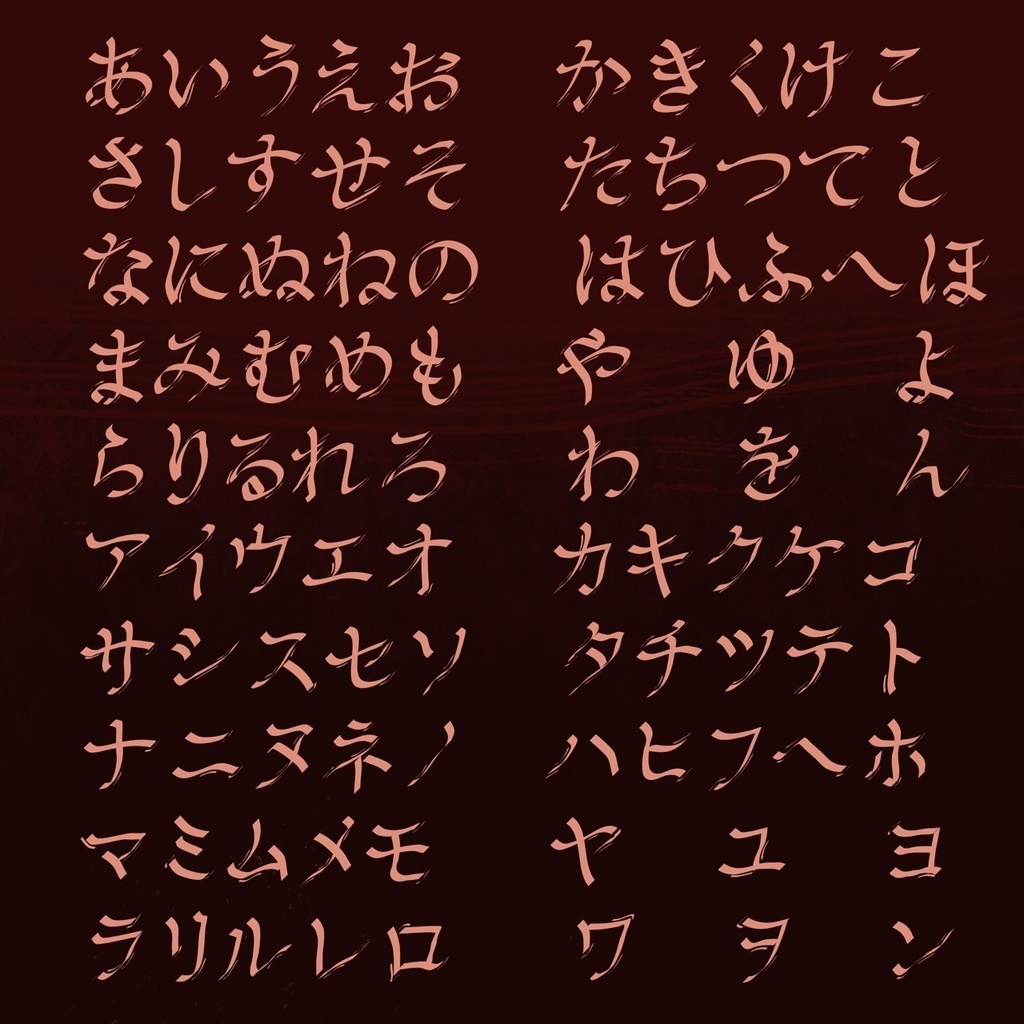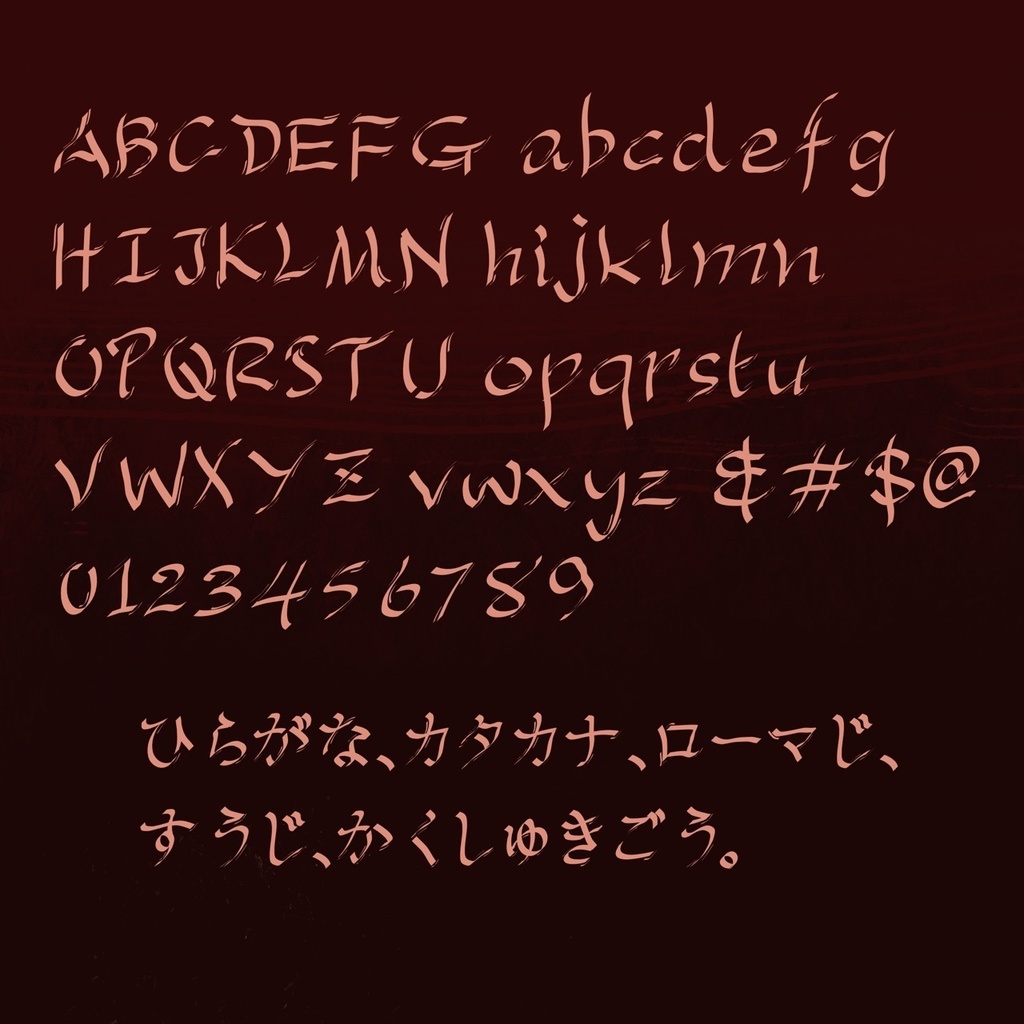
【手書きフォント】プーアルナイフ
ナイフで削ったような独特のかすれを表現した手書きフォントです。タイトルや目次など、大きめのサイズで存在感を発揮します。 ひらがなは明朝体がベースで、どこかレトロな雰囲気もあると思います。 作成に使用したのはiPadのアプリ「iFontMaker」です。
・アルファベット ・ひらがな ・カタカナ ・数字 ・各種記号(少なめです)
・このフォントは縦書きには対応しておりません ・可読性は低めなので、小さいサイズで長文を打つのには不向きです